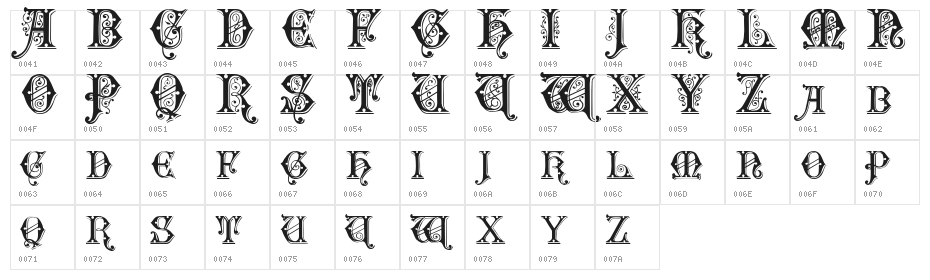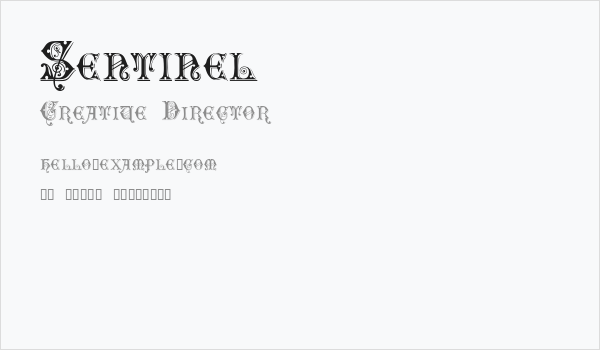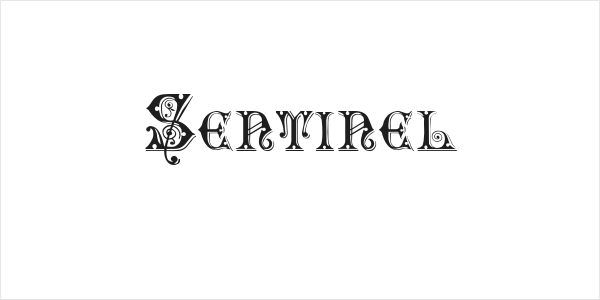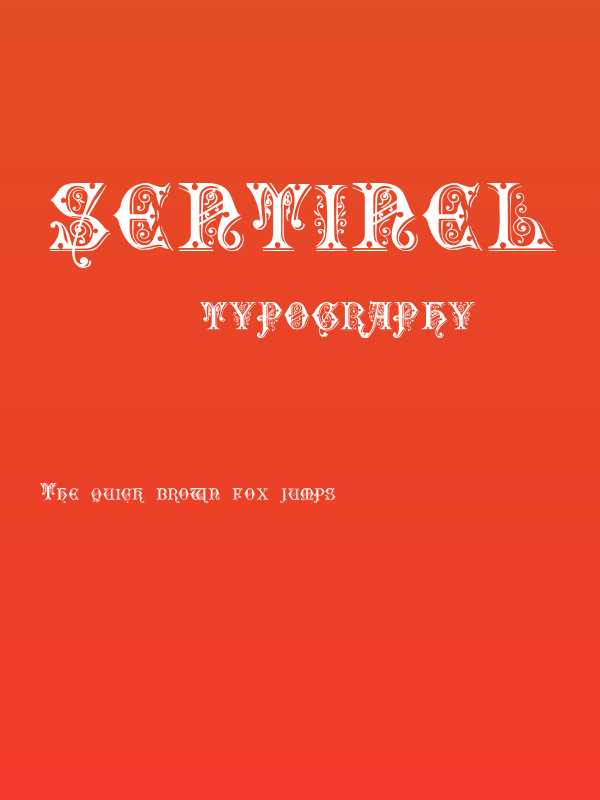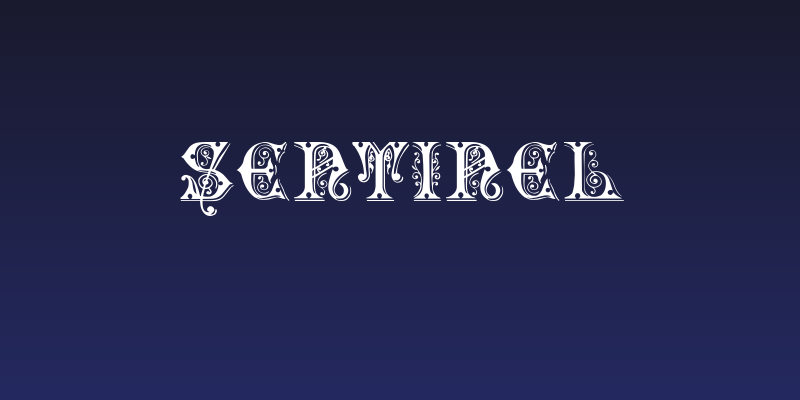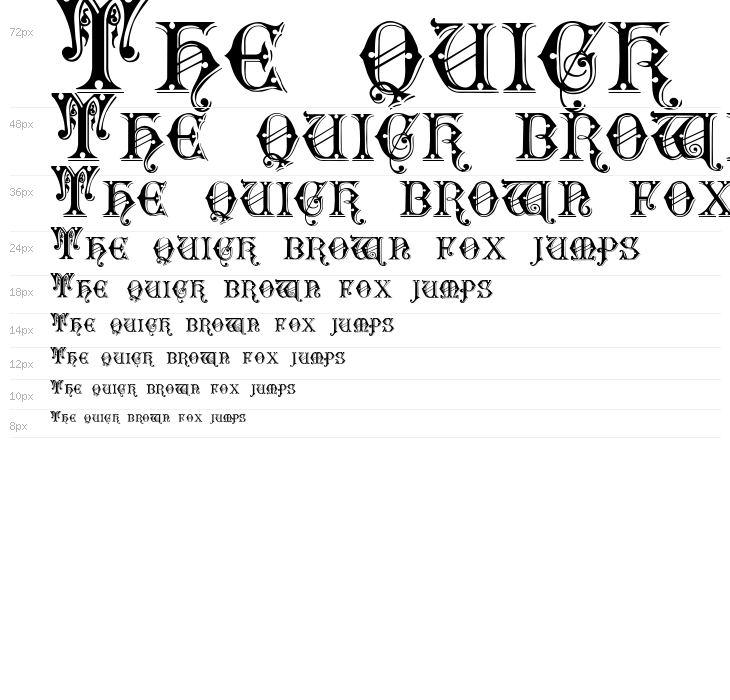
Sentinel Font
Fonts by Dieter Steffmann
| Caso de uso | Logos, Headlines, Decorative text |
| Proyectos propuestos | Ideal for wedding invitations, historical-themed posters, fantasy book covers, and decorative signage. |